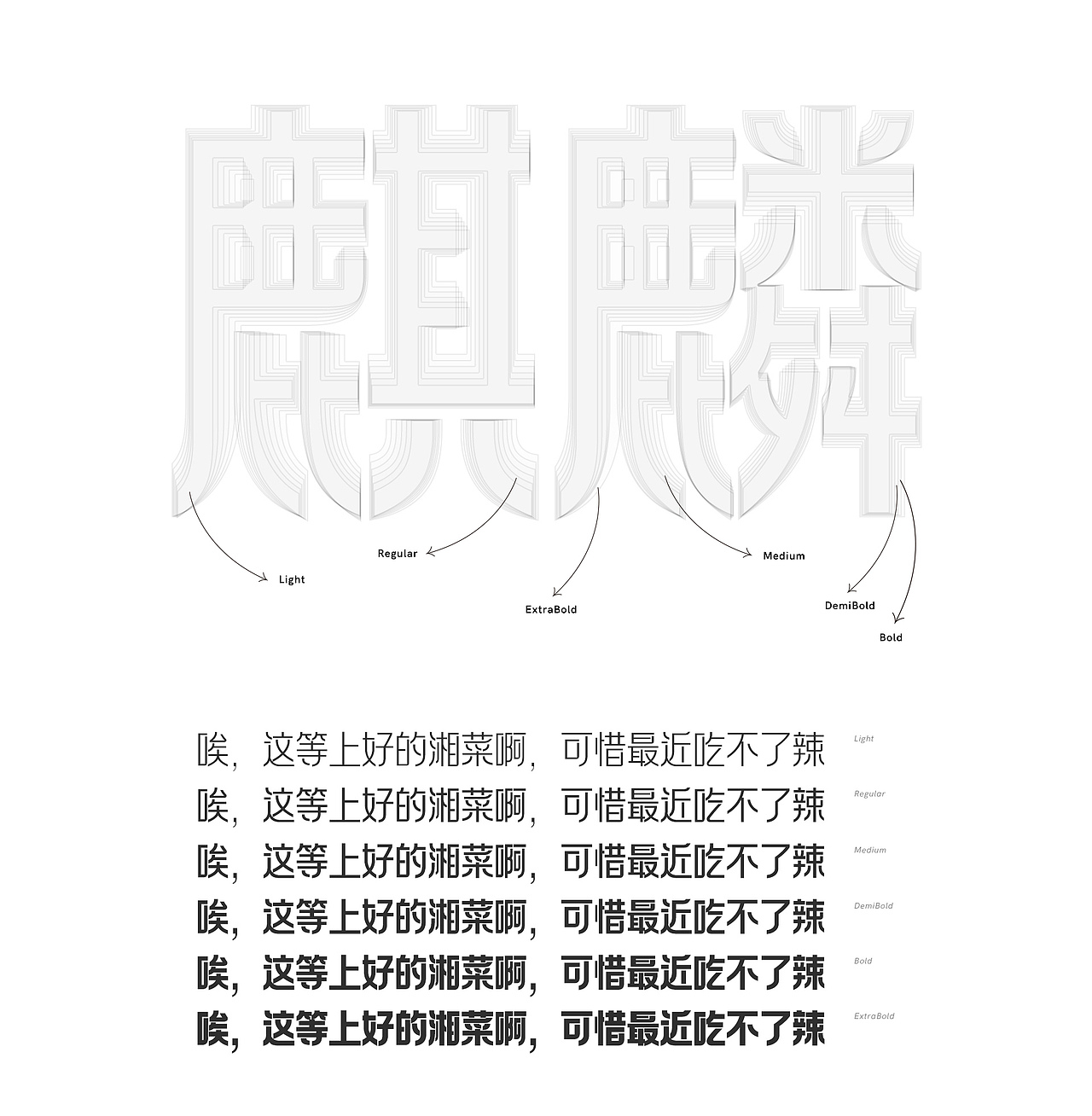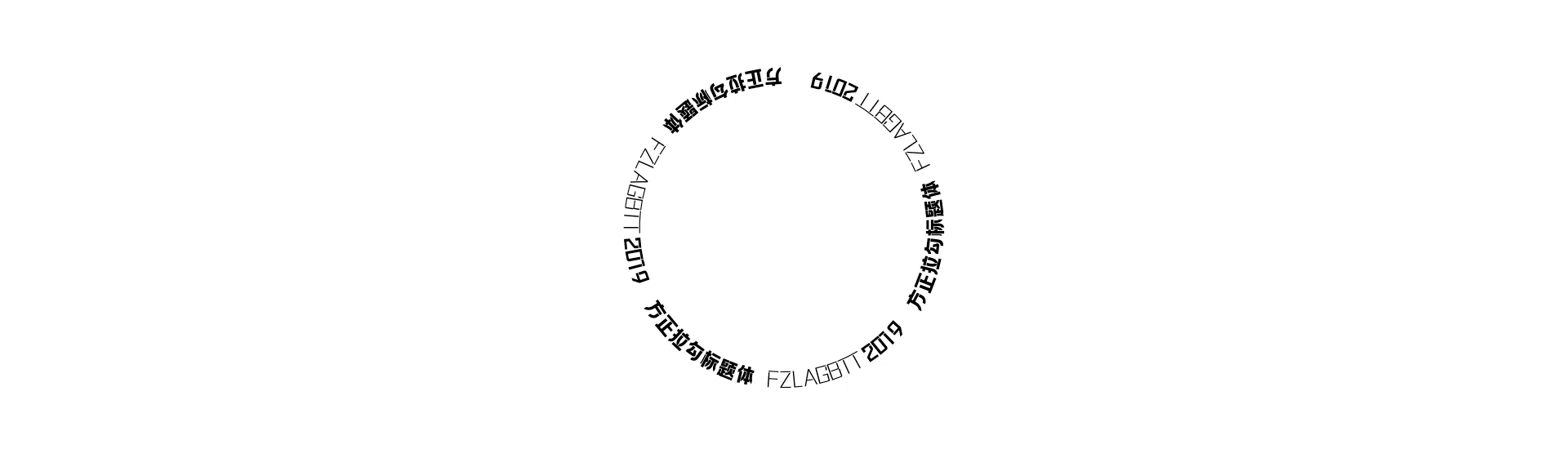
方正拉勾标题体家族(字库)
方正拉勾标题体——承复古风尚,造新潮活力
在2018年的拉勾网“全民升职季”活动中,为强化品牌记忆点、打造个性化品牌形象,拉勾网从重要视觉元素——字体入手,通过打造一套活动专用标准字体,来实现品牌的视觉营销。在经过了定义风格、寻找参考、总结提炼、修改调整、制定规范、批量设计字体小样等一系列锤炼后最终成型。在近两年“全民升职季”招聘狂欢节活动中,此套字体得到全面且广泛的应用。
为了延伸字体价值,赋予其更久远的生命力,拉勾网与方正字库达成合作,以此活动字体为创意基础,开发出一款适用性更广的现代创意字体。最终,方正合作设计师郭炳权先生带领团队完成其产品化,方正拉勾标题体正式面世。
字体创意说明:
方正拉勾标题体是一款针对互联网活动、广告、报刊等媒介而设计的现代创意字体,其字形整体偏矩形化,重心较高,字体端正清朗、气质统一。
方正拉勾标题体在黑体的基础上融入了民国美术字的特点,笔画连接处适当的缺口处理,既保留了旧式印刷广告体的韵味,又注入了新时代的活力;合理的笔画避让使得字体醒目易读,更具识别性。
字库名称:方正拉勾标题体
字库信息:6个字重,每个字重7423字
方正拉勾标题体的风格时尚简洁、识别性强,尤其适用于时效性的广告设计,也可广泛应用于各类报纸、杂志、产品包装、企业VI、影视、互联网等媒介中。
字库创意脱胎于2018年拉勾“全民升职季”12个会场主标题设计,基于此字型特征,经过了定义风格、寻找参考、总结提炼、修改调整、制定规范、批量设计字体小样等一系列锤炼后最终成型。
这套字体包含6款字重,即可用于海报或路牌广告等大型展示场景,也能满足书籍杂志、屏幕阅读等媒介的排版应用需求。
笔画拐角处的导圆处理,字体线条圆滑有美感。
这款字体笔画粗细均匀,撇、捺整体呈镜像对称,笔画转折采用“外圆内方”的设计,内部折角方直,风格果敢;外部的拐角处则进行了导圆处理,线条圆滑,字形整体更具美感和丰富性。
合理的笔画避让,字体清晰易读。
( 字体应用概念海报再创作:左为日本台风告急地铁站照片)
方正拉勾标题体在黑体的基础上融入了民国美术字的特点,笔画连接处适当的缺口处理,既保留了旧式印刷广告体的韵味,
又注入了新时代的活力。
(应用展示)